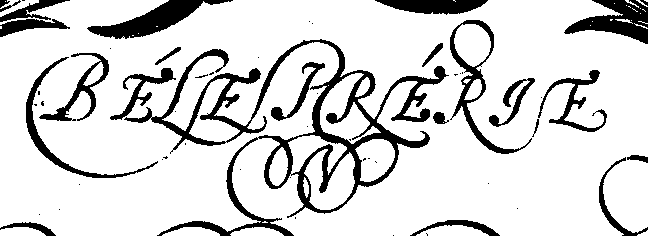
Louis Grammont wrote: > > > Une des raisons de la carence de nos instituteurs ne viendrait-elle pas > du fait que les belles lettres en script capitale qu'ils crayonez au > tableau noir ne s'accentuent pas obligatoirement ? Rarement il est vrai, mais il ne faut pas croire que c'est jamais : ci-attaché un extrait de la couverture du livre Béle Prérie (anagramme de son auteur : Pierre Le Bé) qui date de 1601 (réédition de Tschichold en 1974. -- Jacques André, Irisa/Inria-Rennes Campus de Beaulieu, F-35042 Rennes Cedex, France Tél. : +33 2 99 84 73 50, fax : +33 2 99 84 71 71 email : Jacques.Andre@xxxxxxxx